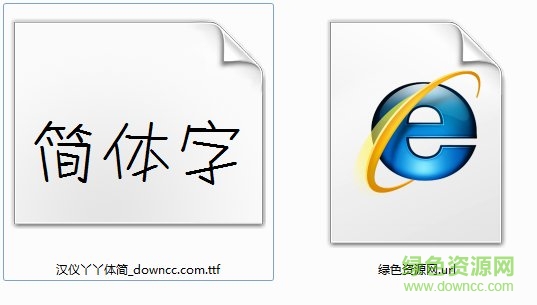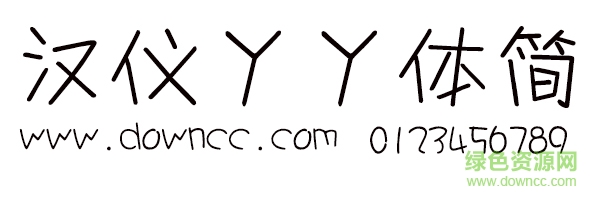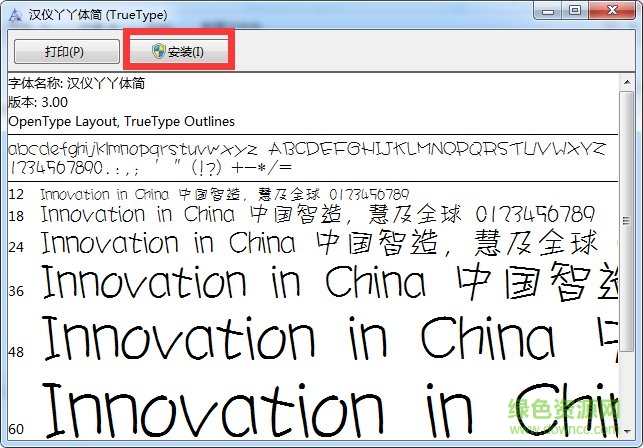
漢儀丫丫體簡ttf是一個免費的字體資源,本字體非常的卡通化,可用來設計一些兒童畫冊等比較卡通的平面圖。能夠在win7、win8、xp以及win10主流系統(tǒng)上安裝使用!歡迎下載體驗。
漢儀丫丫體全稱是漢儀丫丫體簡,就如名字一樣。丫體擁有手寫、調皮等字體風格,非常有個性,就像小孩子剛學習寫字時寫出的字體,支持中文簡體、數(shù)字、英文字母、符號等輸出模式,并且完全符合大部分用戶審美標準,適合應用在廣告設計、圖片制作等多種場景中。